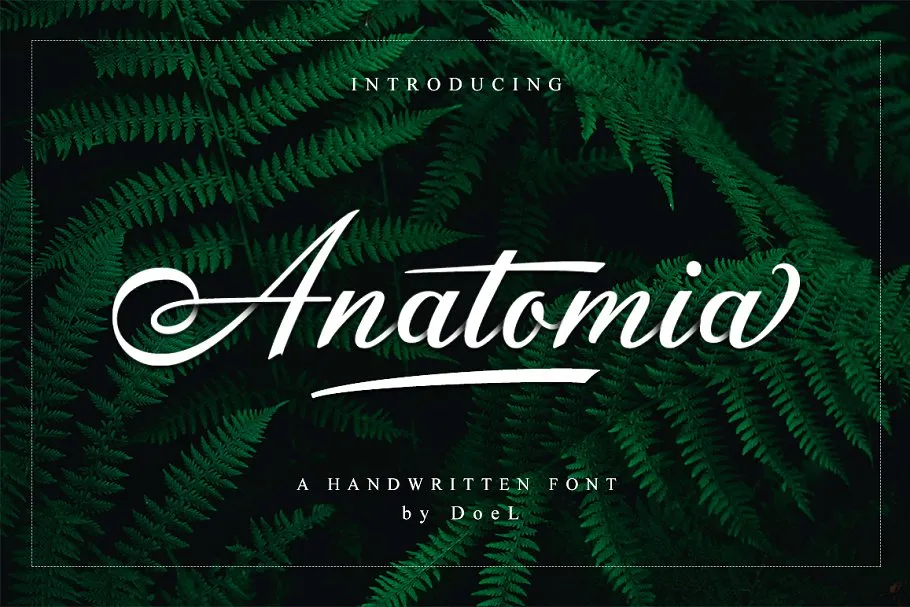
Anatomia Script Font
Anatomia Script Font é uma nova descoberta para entusiasmados com letras manuscritas. Esta font oferece um toque natural, sofisticado e perfeito para qualquer projeto que exija a elegância do script. Com Anatomia, você tem acesso a uma fonte aberta de alta qualidade, adequada tanto para criações visuais quanto para aplicações comerciais variadas. Este é um estilo moderno com muitas alternativas, perfeitamente adaptado para nomes e logotipos, selos corporativos, convites de casamento, títulos criativos, rótulos, posteres ou até mesmo como uma fonte única em estandartes. Anatomia combina a beleza da arte do escritório com o estilo moderno que você tanto deseja, tornando-o um recurso ideal para qualquer projeto onde um toque de elegância é desejado. Com seu design único e sua variedade de aplicações, a Anatomia Script Font é uma ótima adição à sua paleta de recursos gráficos. Este novo estilo de escrita moderna, natural e sofisticada é perfeito para quem busca um toque especial em seus projetos.